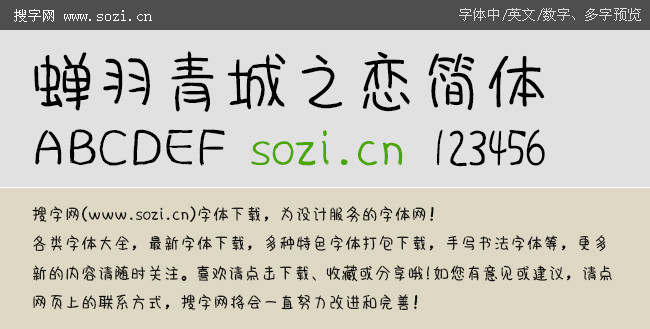
蟬羽青城之戀簡(jiǎn)體
搜字網(wǎng)提供一款蟬羽青城之戀簡(jiǎn)體中文字體下載,蟬羽寶寶蟬簡(jiǎn)體是一款個(gè)性手寫字體,字形活潑可愛、布白均勻,整體風(fēng)格輕柔舒緩,給人簡(jiǎn)潔舒適的視覺美感,能夠適用于藝術(shù)設(shè)計(jì)、包裝印刷、簽名設(shè)計(jì)、圖形設(shè)計(jì)等領(lǐng)域。(本字庫(kù)版權(quán)歸王建剛個(gè)人所有,商用需經(jīng)作者許可)